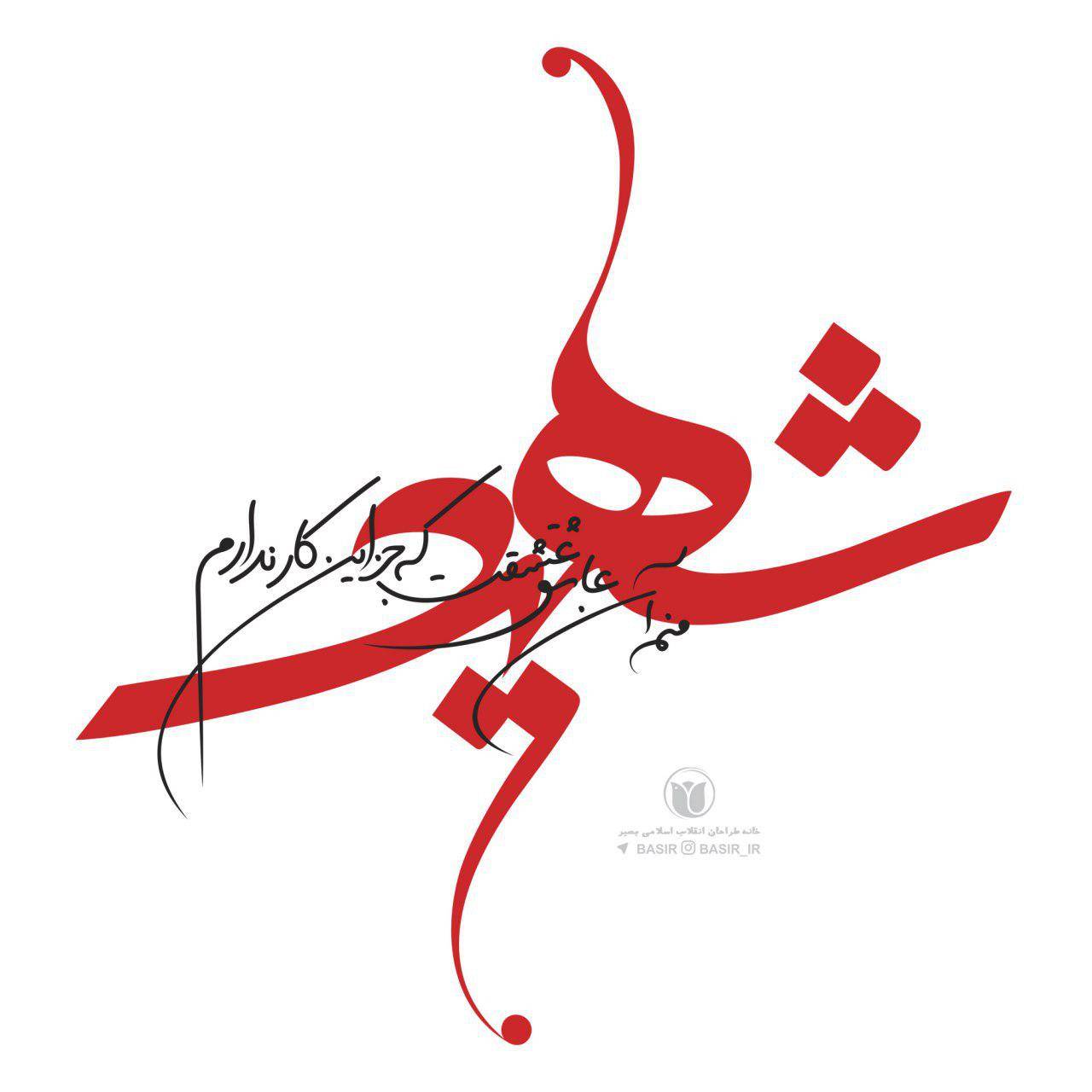
فونت مهرگان
فونت دست نویس مهرگان
فونت دست نویس مهرگان برای نخستین بار از طریق سایت ایران فونت منتشر می گردد. طراحی فونت مهرگان توسط آقای محمد عموئی بر اساس دست نوشته های خانم بهار تقربی از ابتدای سال 1395 آغاز و تا پایان خرداد 1396 ادامه داشت. در طراحی این فونت با بررسی و الگوبرداری از دست نوشته ها سعی شده که حس نوشت با دست برای مخاطب تداعی گردد.
این فونت یکی از ظریف ترین و دلنشین ترین فونتهای دست نویس موجود فارسی است. از این فونت میتوان در عکس نوشتها استفاده کرد. برای لوگوتایپ ها بی نظیر است. در کارهای گرافیکی و طراحی جلد فوق العاده جذاب و خواناست. البته برای متون طولانی توصیه نمی کنیم. ولی برای تیترهای که دوست دارید صمیمی باشند انتخاب خوبی است.
فونت مهرگان با یه دست کاری ساده و خلاقانه فونتی عجیب